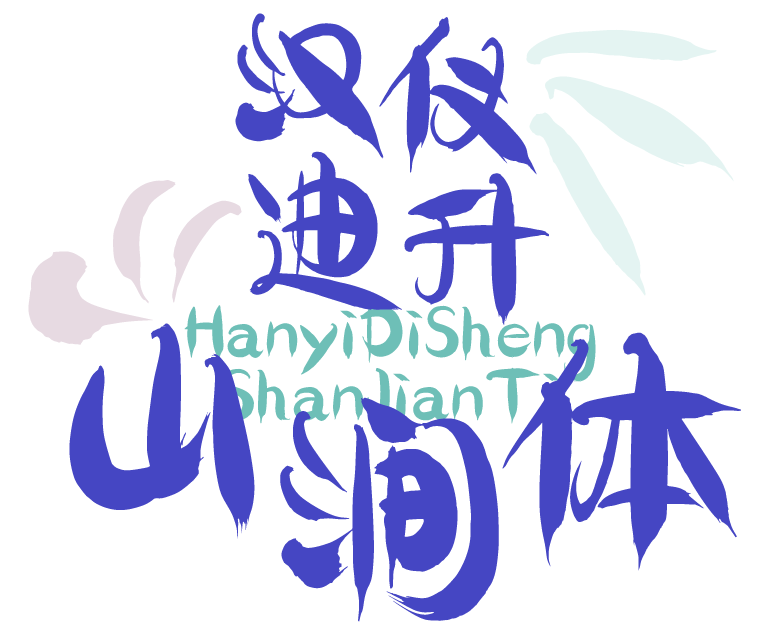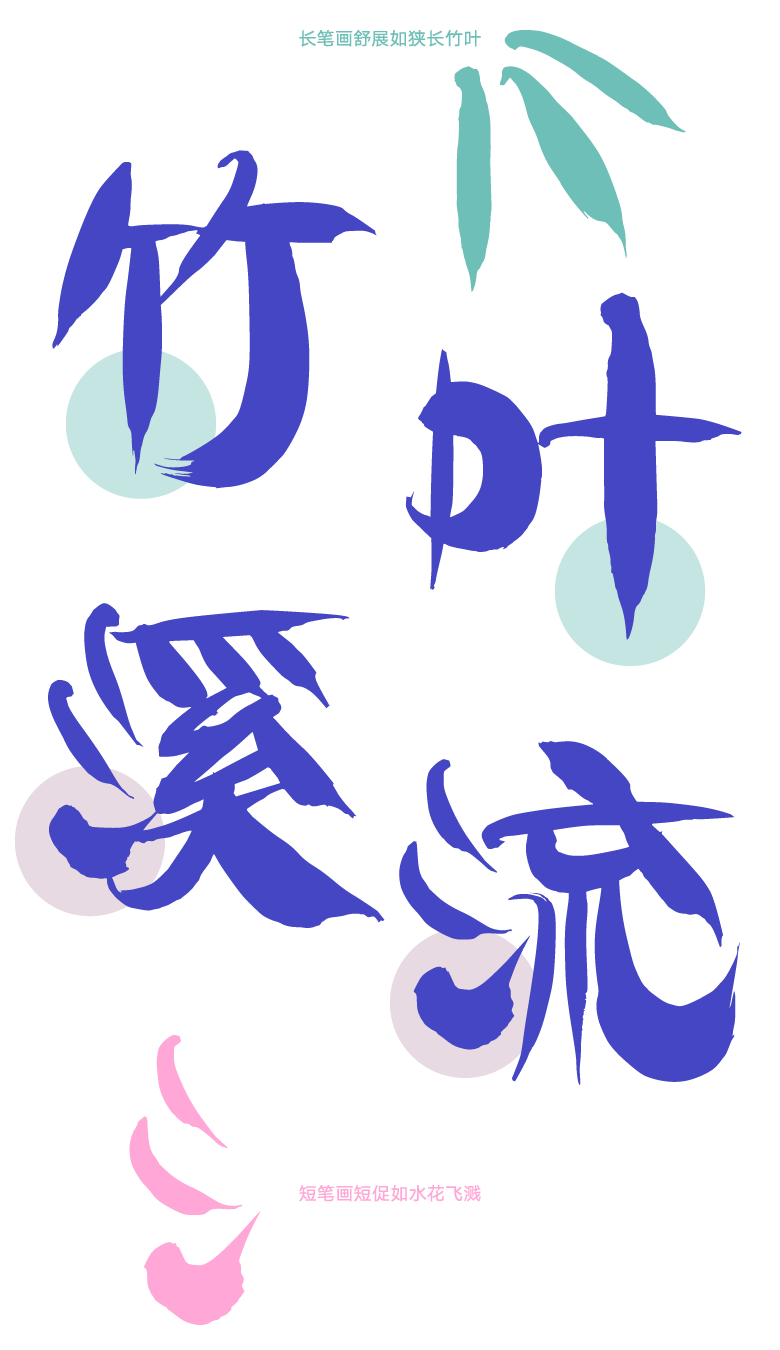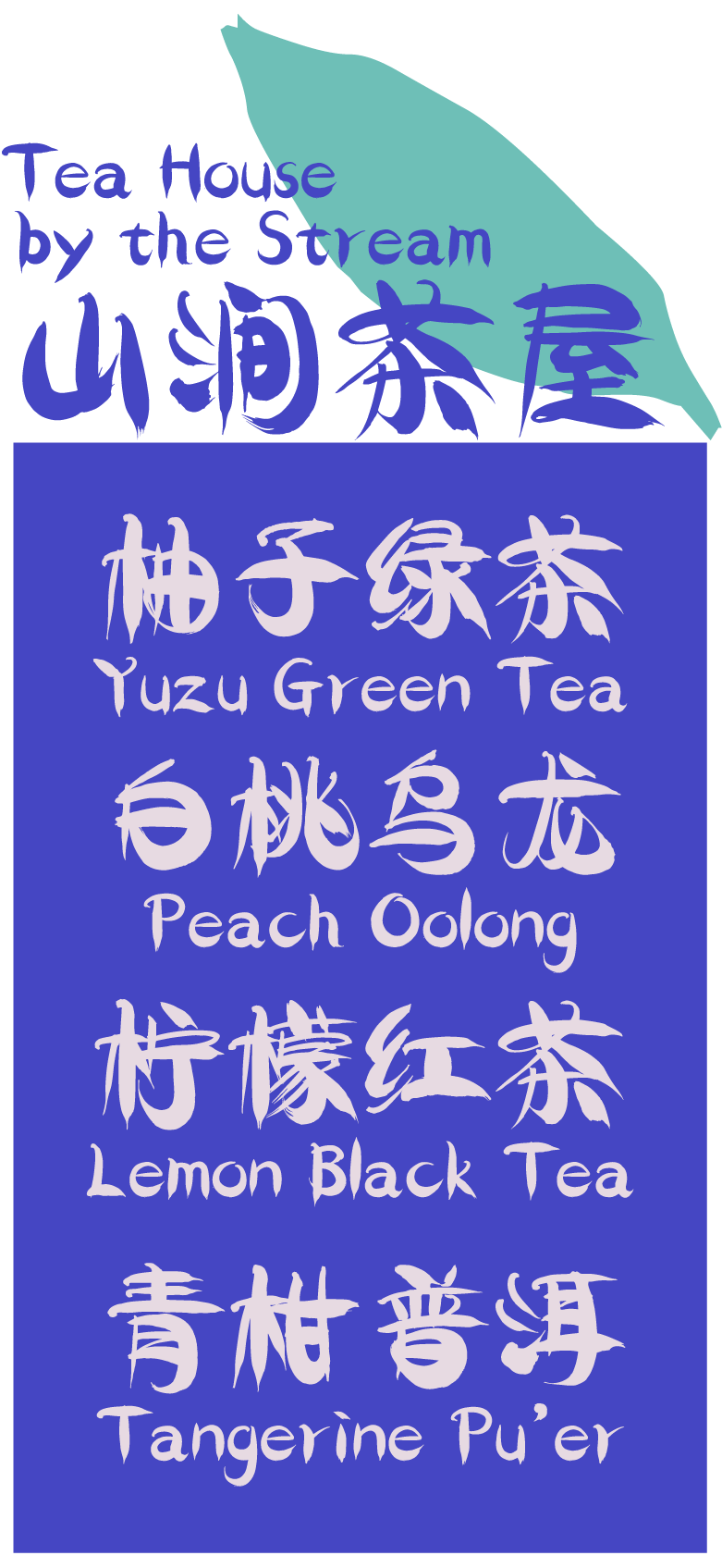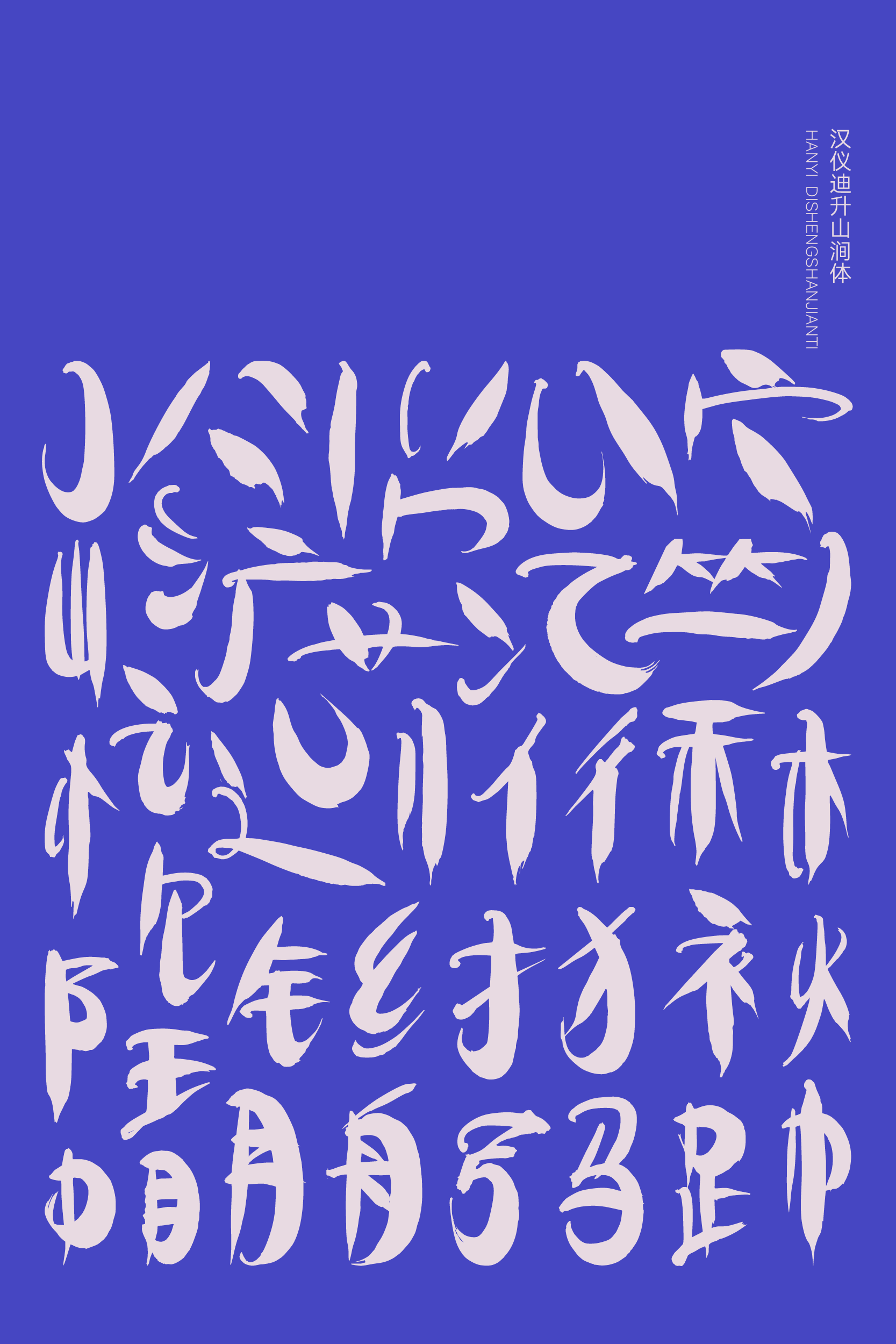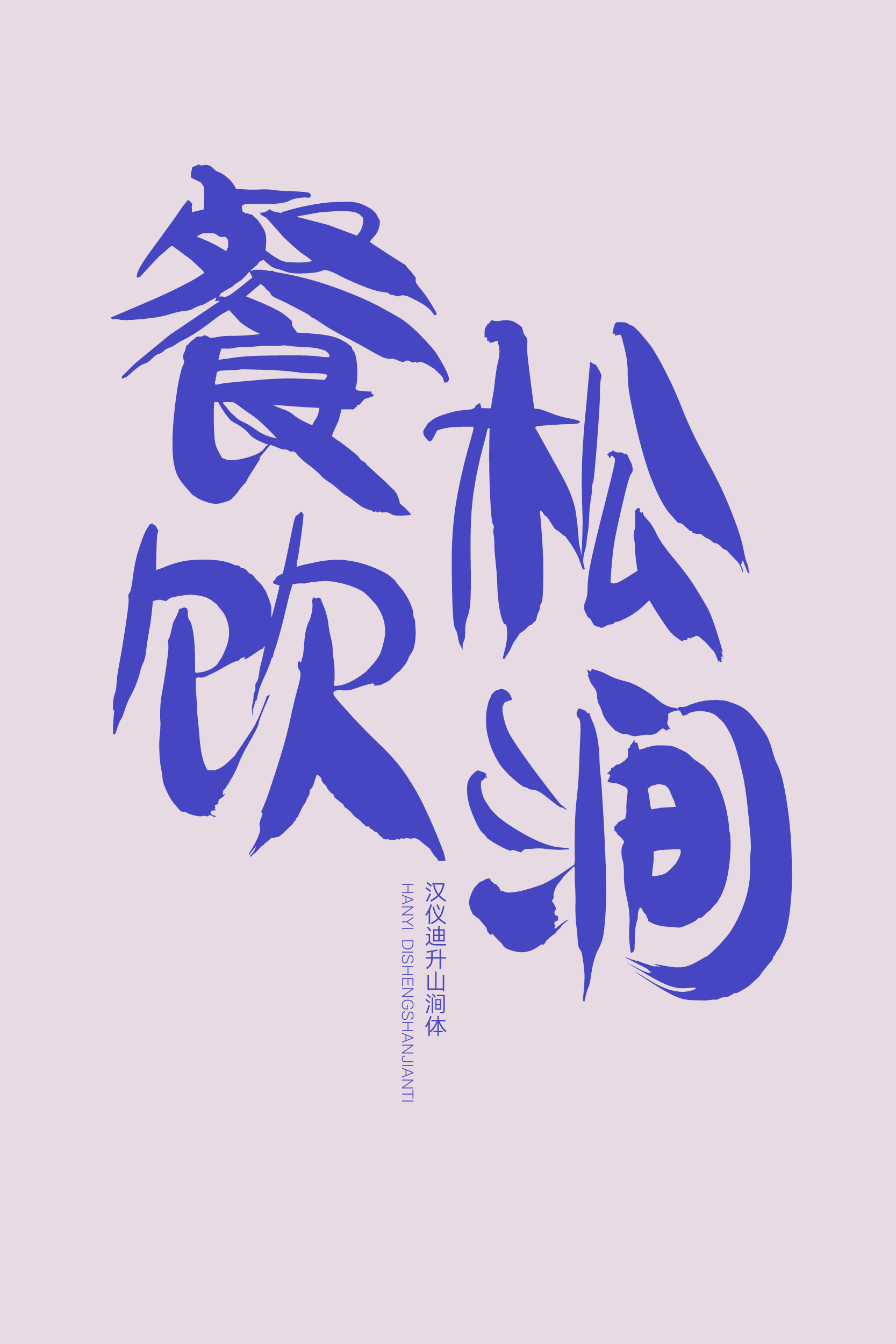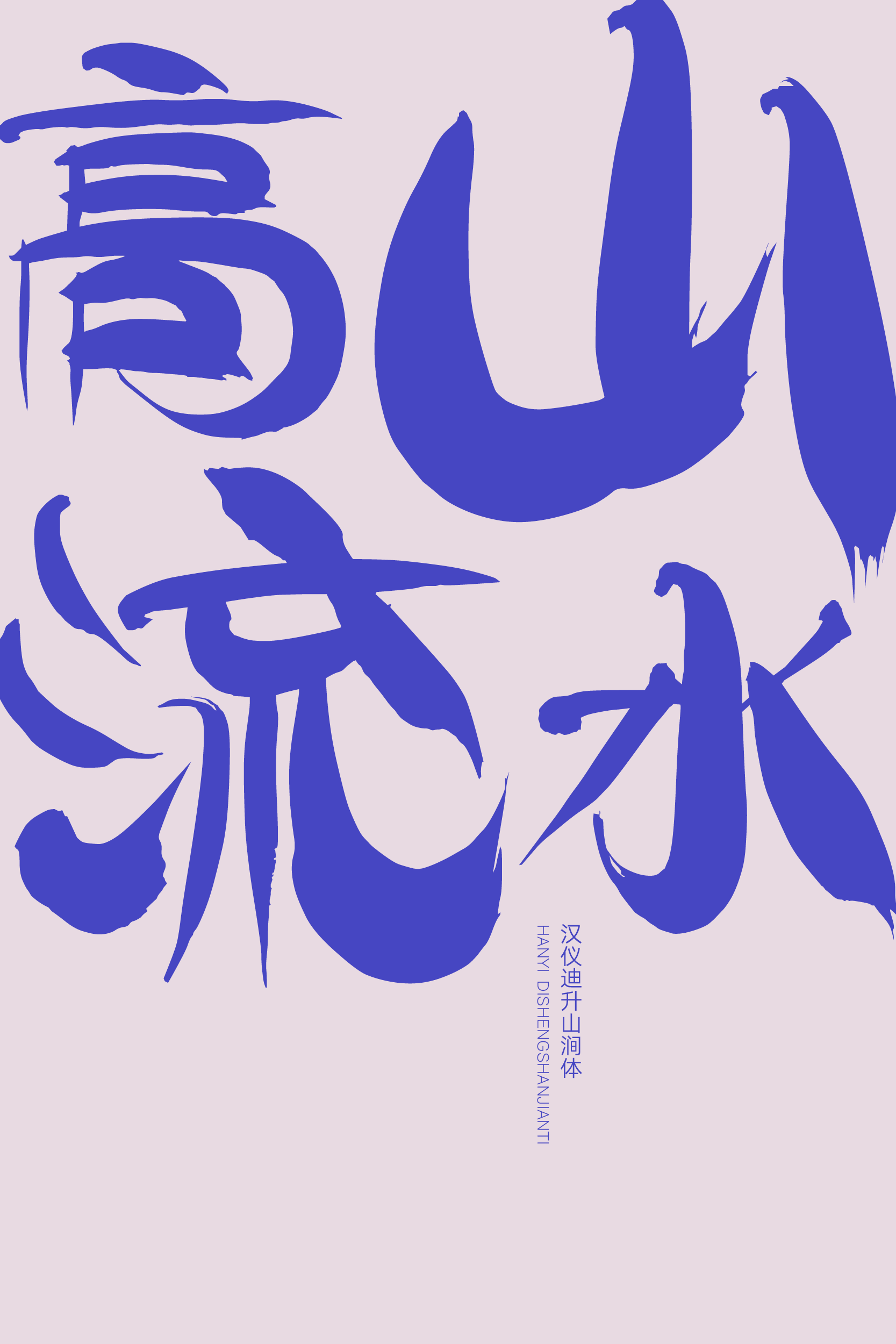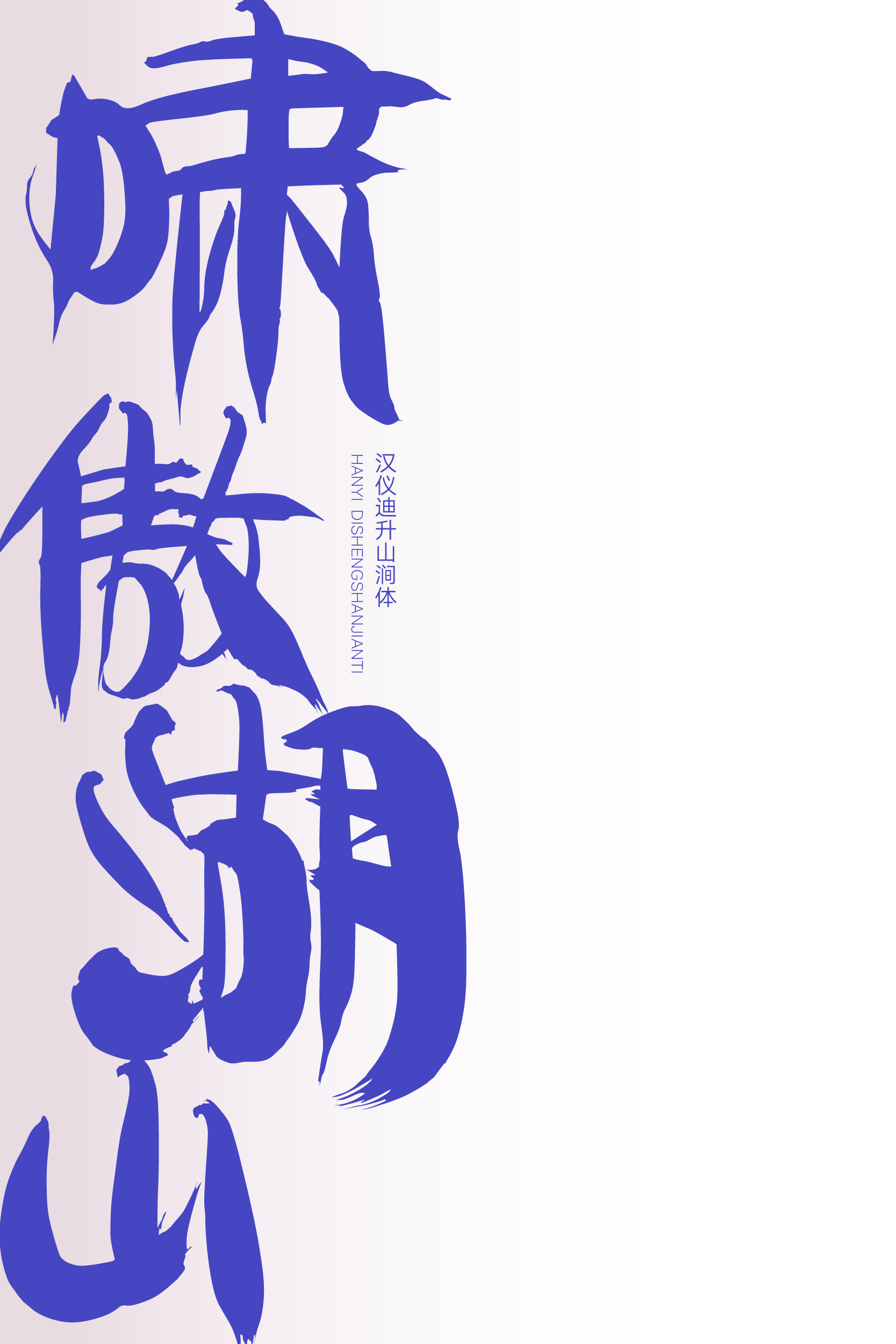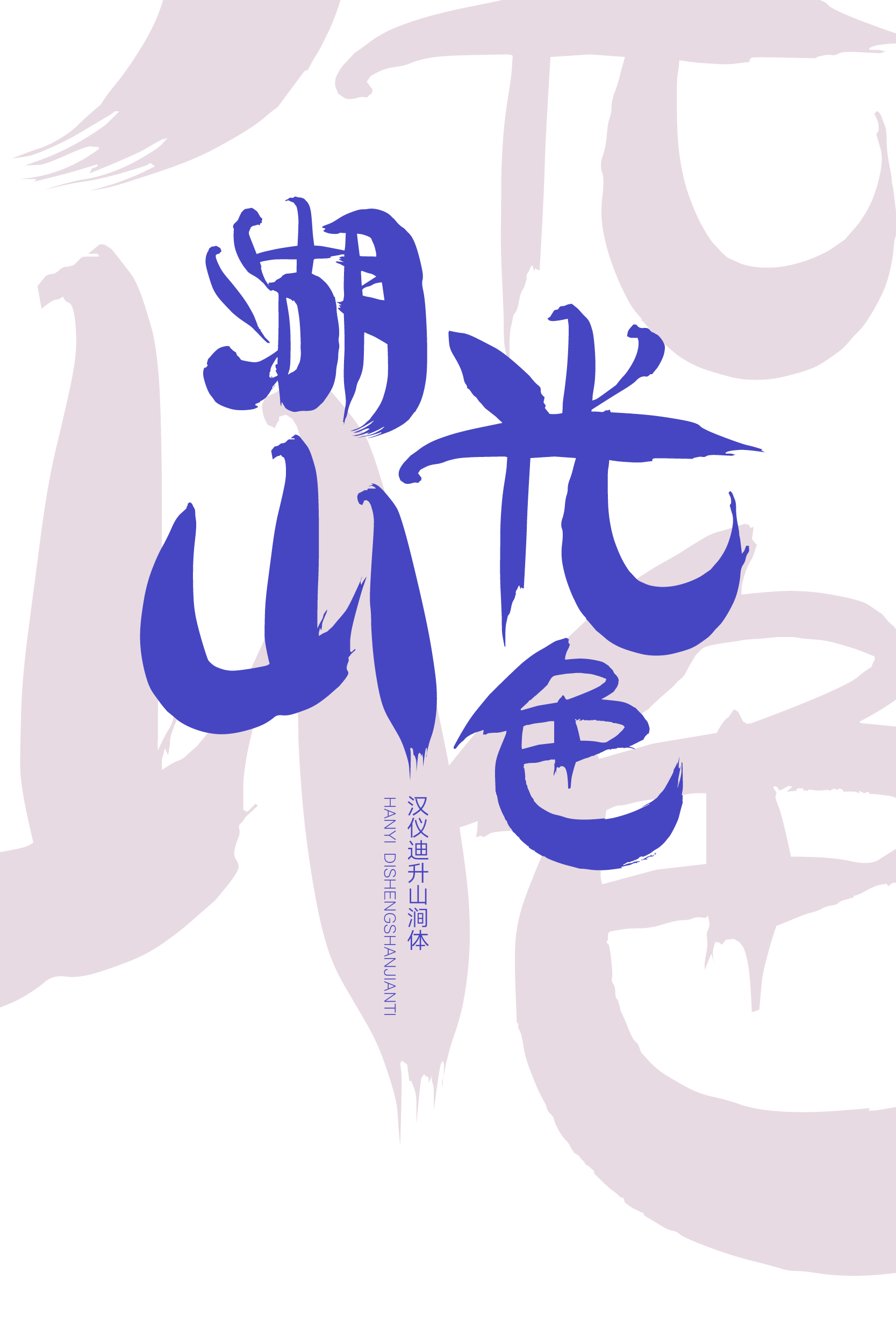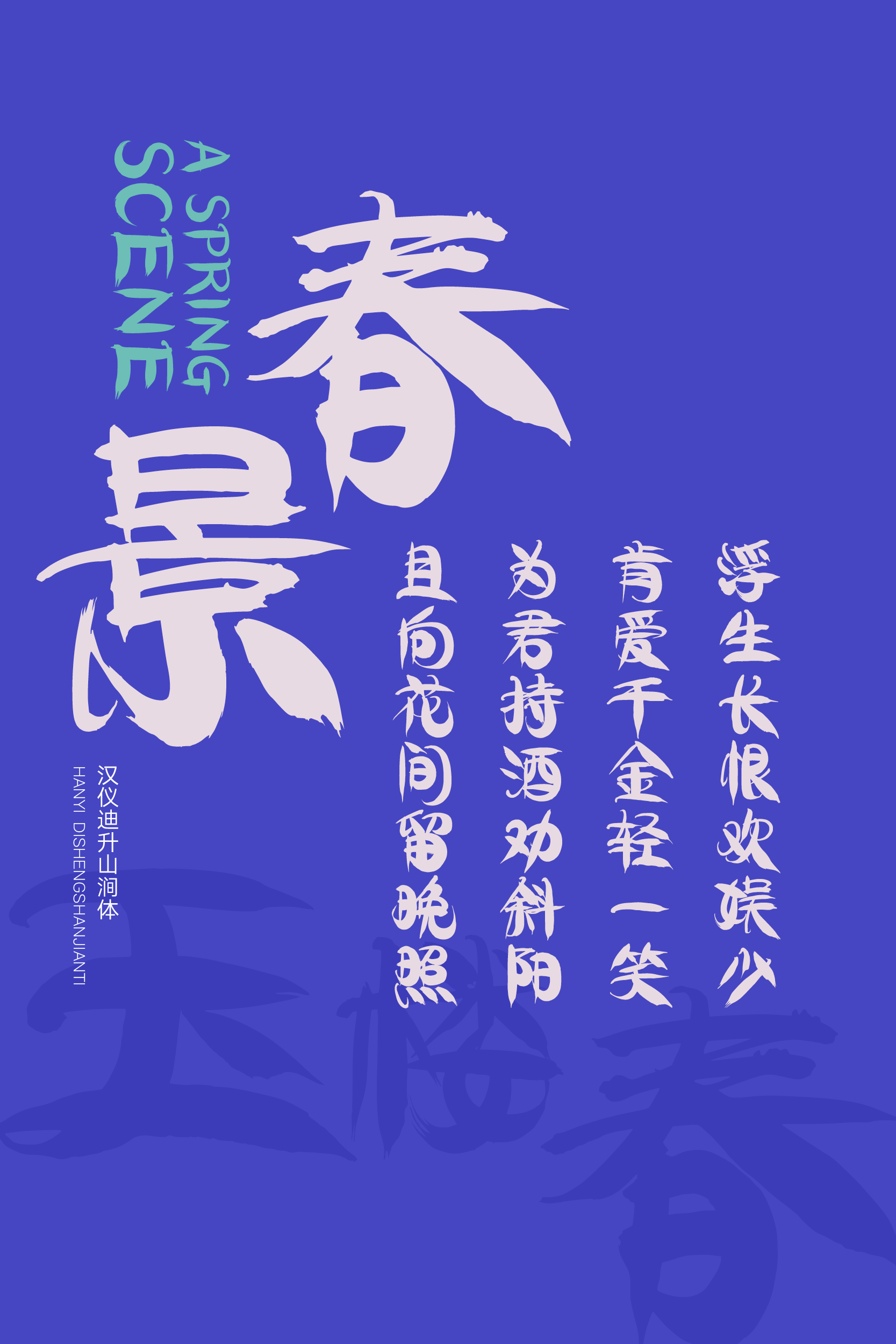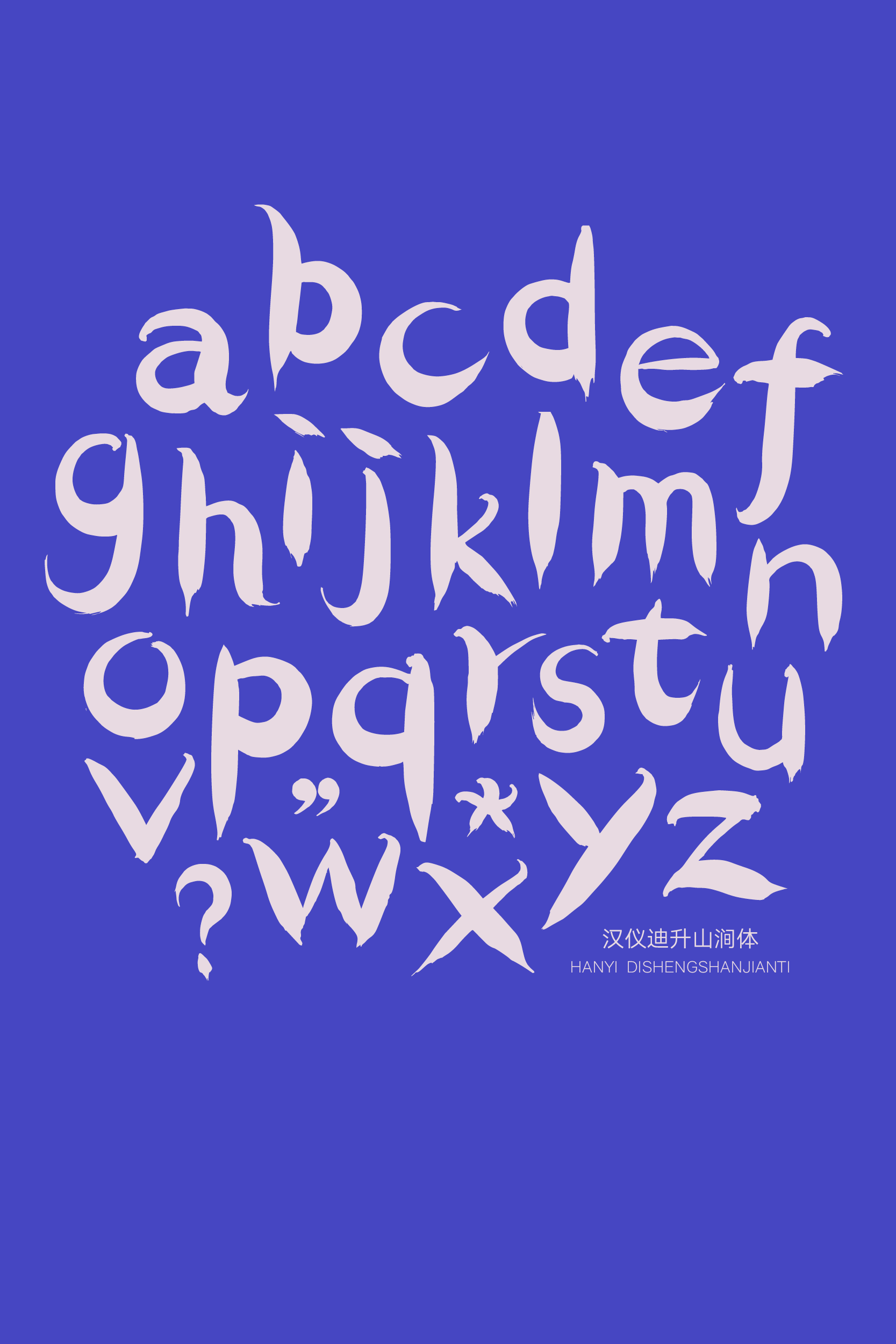
仿佛置身于山涧中的书写字体
书写字体
汉仪迪升山涧体是由汉仪字库签约作者迪升创作的一款颇具自然气息的书写字体。繁密朴茂、郁郁苍苍,字形饱满,笔画圆而凌厉,行笔间显露出速度感。这款字体渲染出山涧之空灵野逸,适用于生态自然、休闲餐饮、度假娱乐等多种使用场景,令人仿佛置身于山涧中,呼吸着清新的空气。
字形饱满,重心偏高,顶部略窄,底部浑圆。
笔法自然朴茂,郁郁苍苍。笔画圆而凌厉,行笔间显露出速度感。
汉仪迪升山涧体的西文部分取中文上提饱满的字形和清新朴茂的笔法,中西文匹配自然和谐。
汉仪迪升山涧体渲染了空灵野逸的氛围,联结种种自然意象,在与自然生态环境和休闲餐饮娱乐相关的使用场景中具有极佳的表现力。